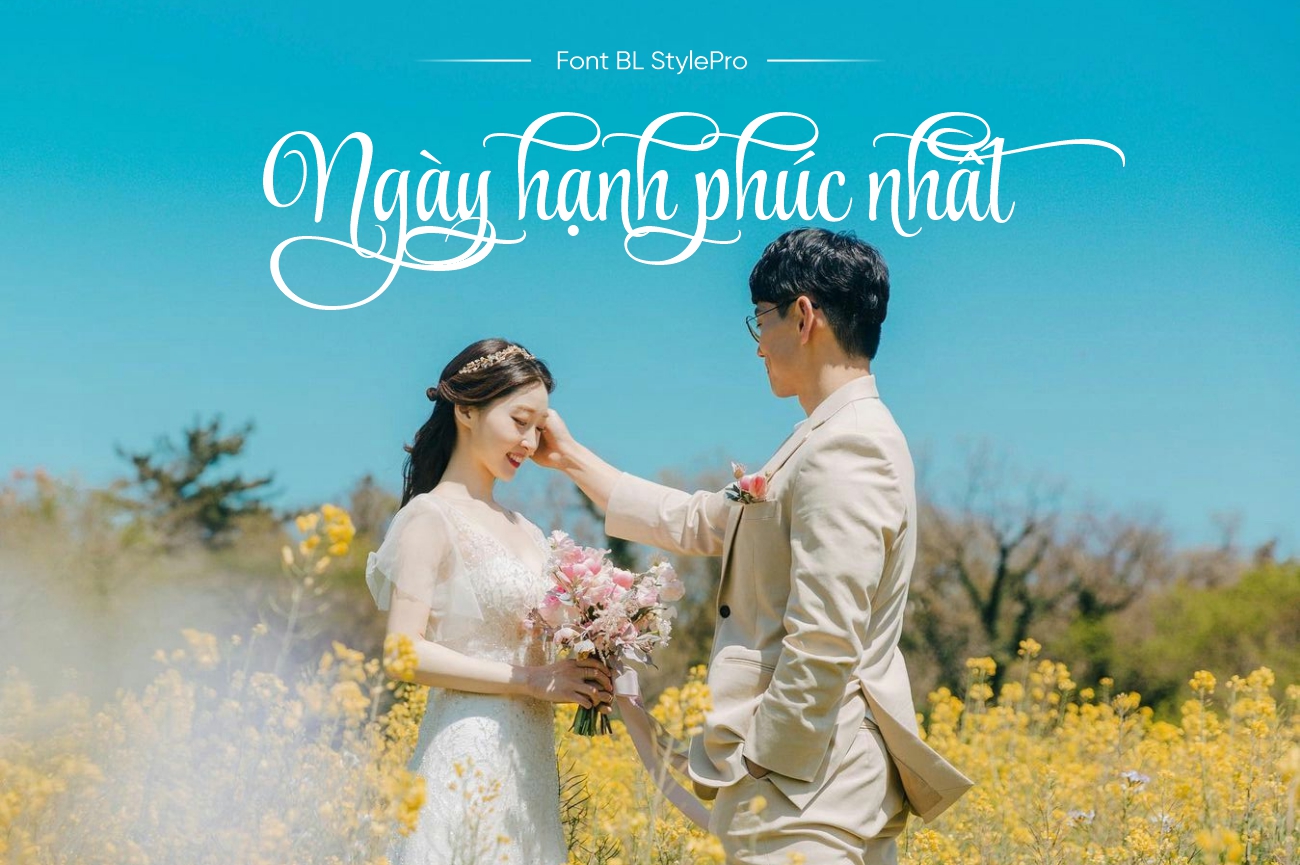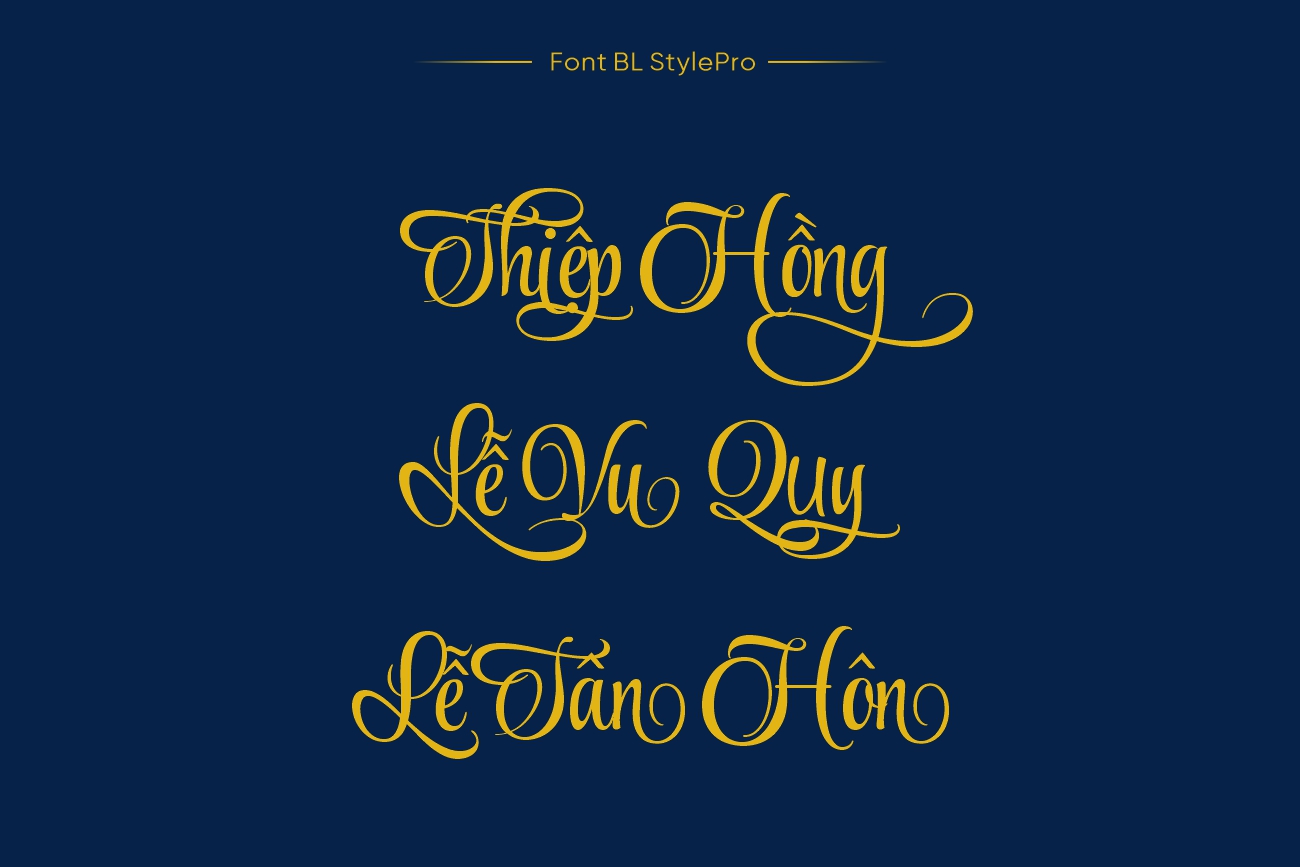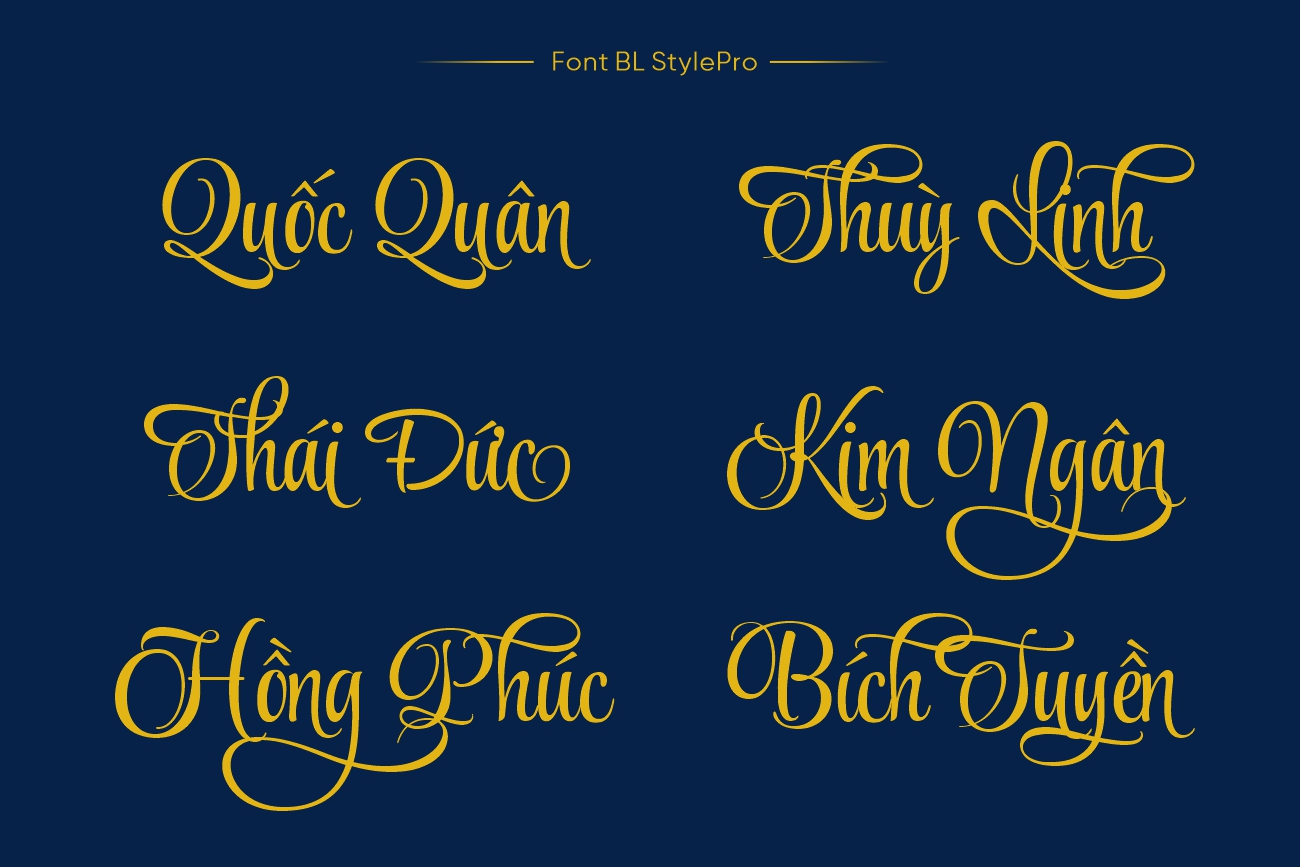
BL StylePro - Font chữ viết tay nghệ thuật
Ưu điểm của font BL StylePro
Đường nét mượt mà, chữ viết tay giả thư pháp giúp tạo cảm giác sang trọng, thân thiện và cá nhân hóa.
Có các chi tiết cách điệu (swash, flourish) giúp tăng tính trang trí khi dùng làm tiêu đề, lời mời, thiệp cưới.
Khi dùng cho tiếng Việt: nếu bạn tìm được “BL StylePro” là có thể là bản đã việt hóa hoặc mở rộng kiểu chữ cho tiếng Việt — nên cần kiểm tra bảng ký tự (glyph) có hỗ trợ dấu tiếng Việt đầy đủ hay không.
Kết hợp: Vì StylePro đã khá nổi bật rồi nên khi dùng nên kết hợp với một font sans-serif đơn giản để tạo cân bằng.
Tiếng Việt: Nếu bản gốc không hỗ trợ dấu tiếng Việt đầy đủ, cần xem bản Việt hóa hoặc chọn phiên bản hỗ trợ tiếng Việt.